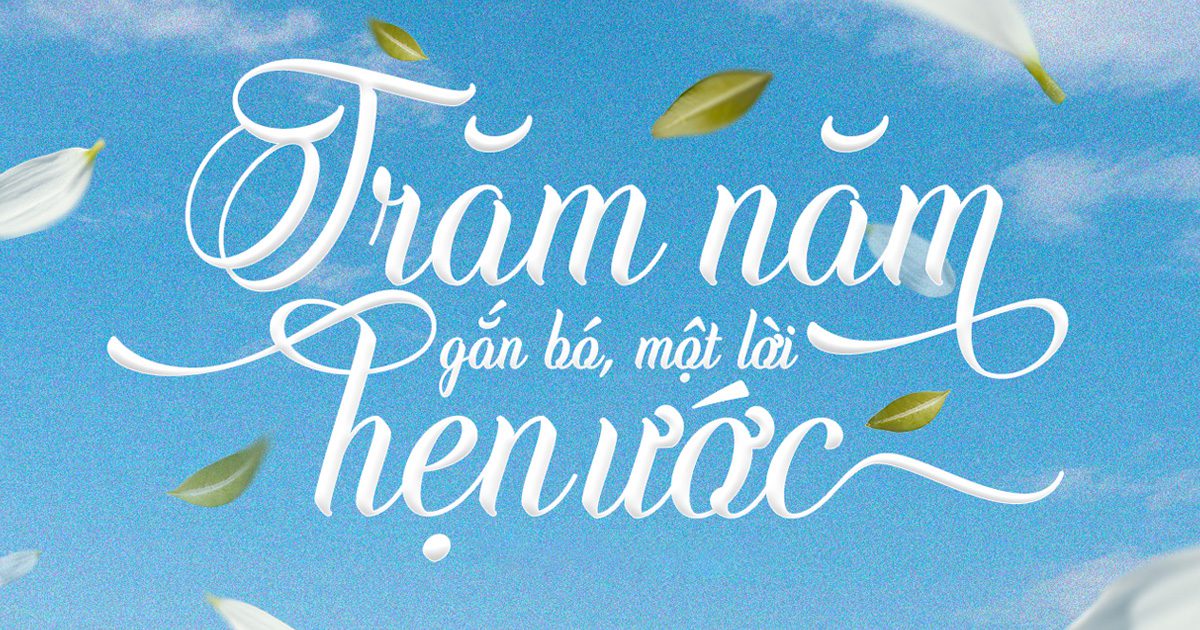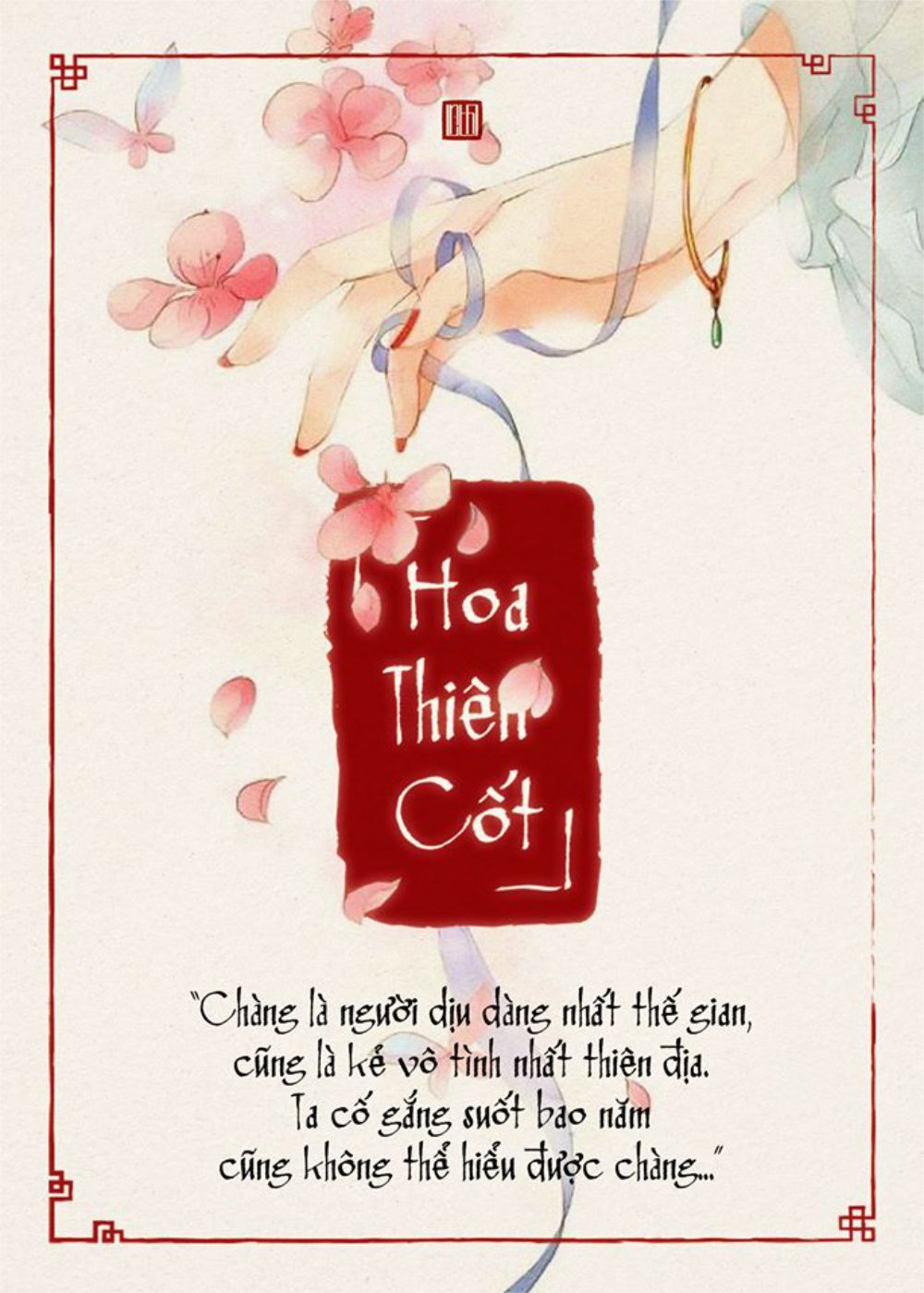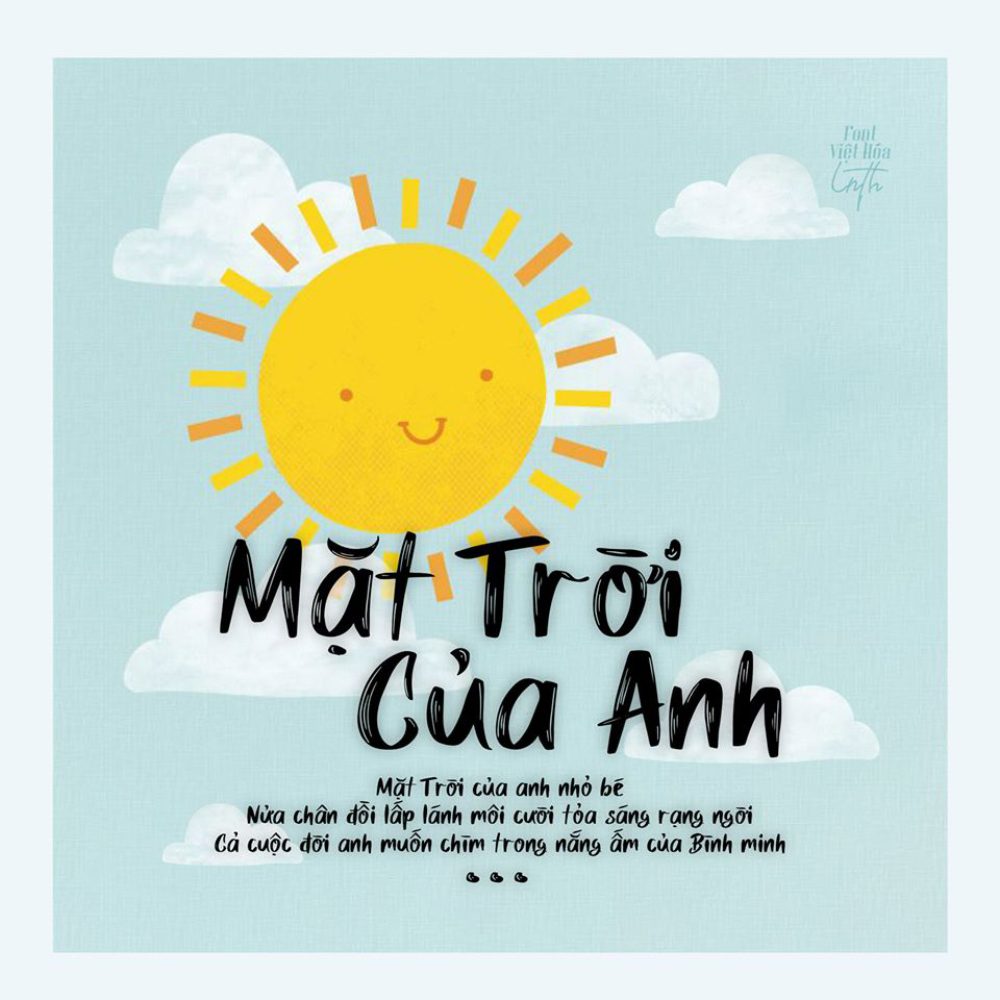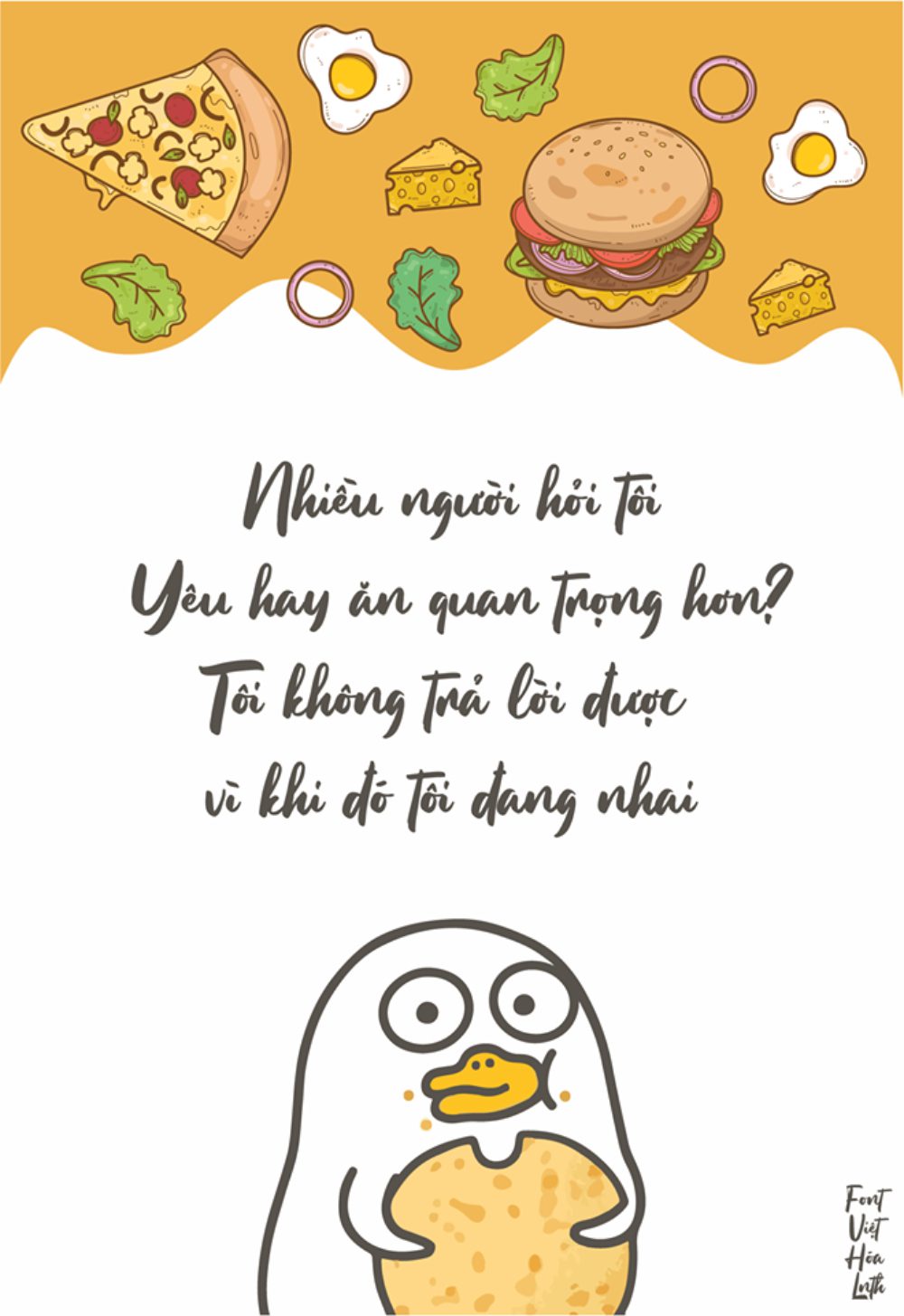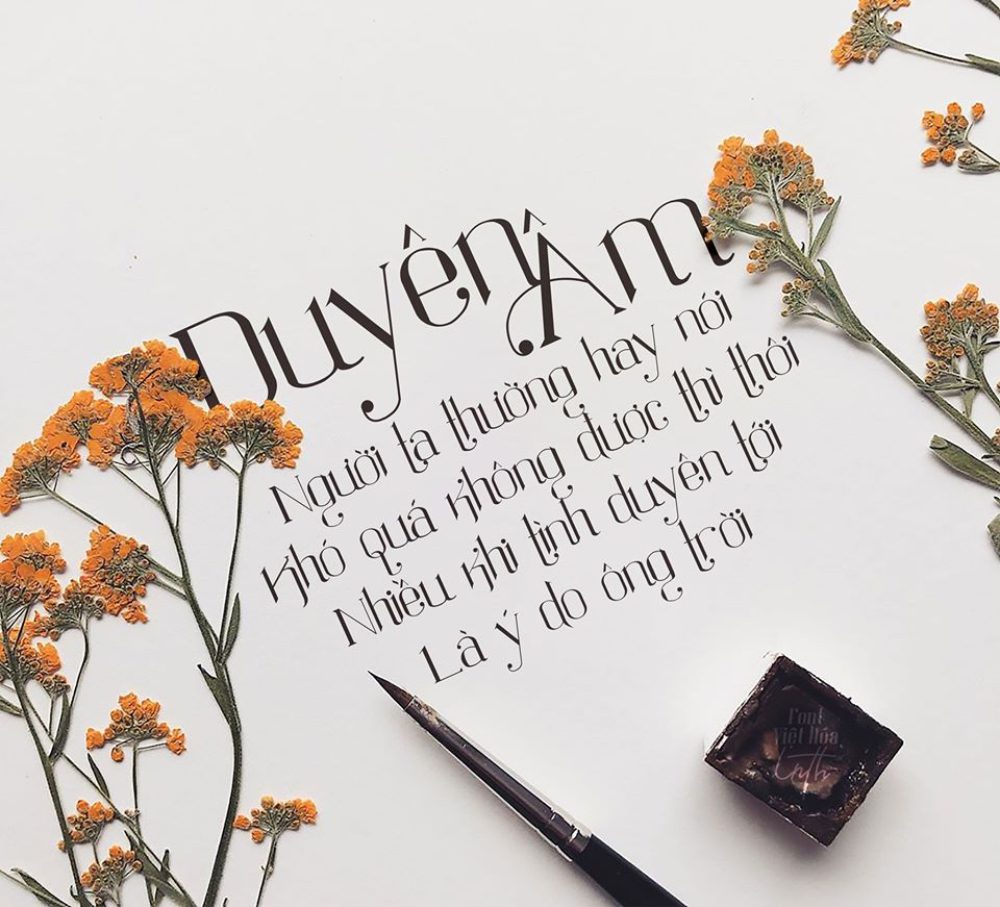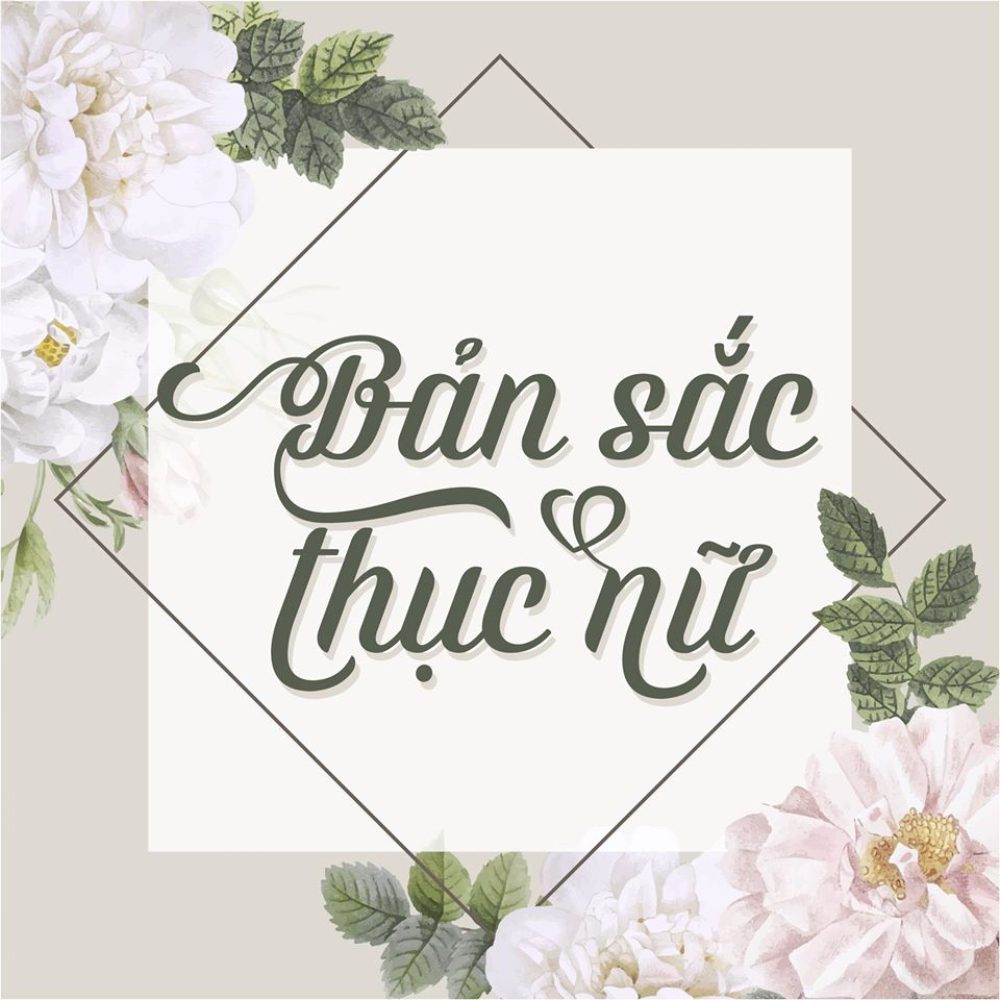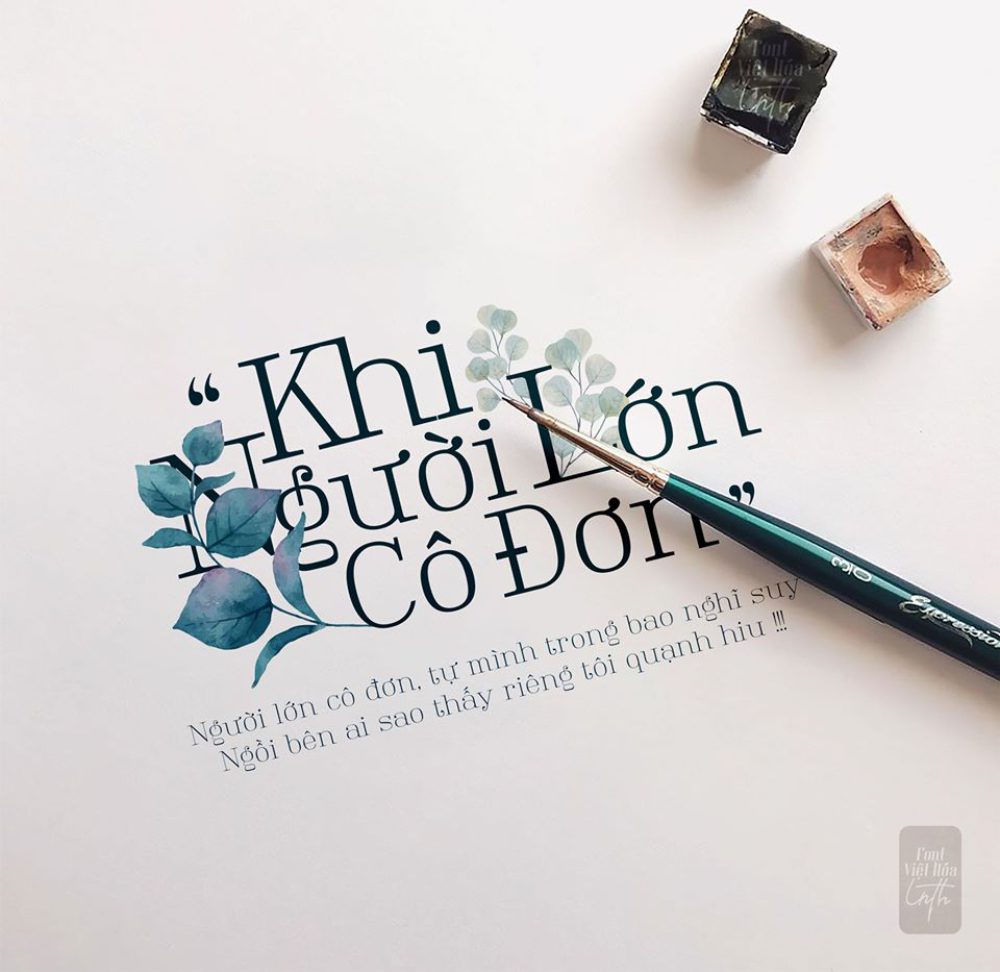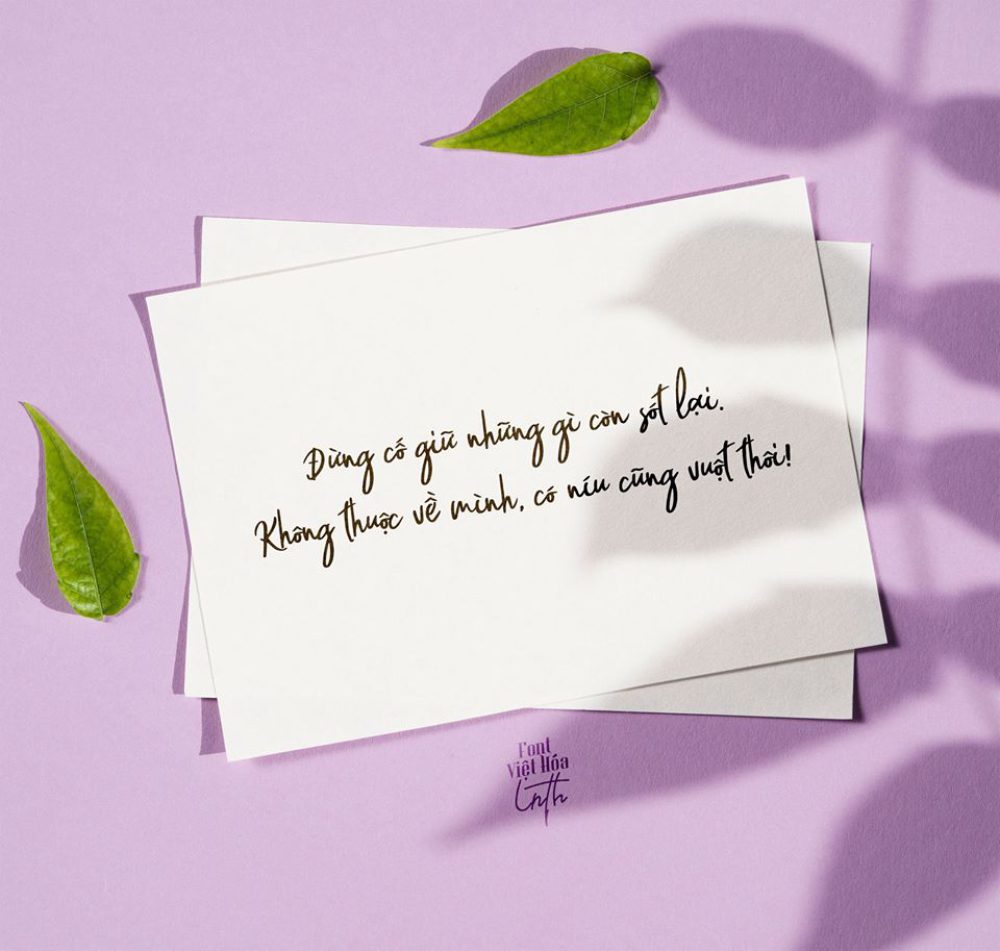
Font Việt Hóa Miễn Phí 39 Font LNTH Cho Designer
Font Việt Hóa Miễn Phí 39 Font LNTH cho designer là bộ tài nguyên chữ rất hữu ích dành cho những ai thường xuyên làm việc với thiết kế đồ họa, truyền thông, branding, poster, banner, social media hoặc các ấn phẩm sáng tạo. Trong thiết kế, font chữ không chỉ có nhiệm vụ hiển thị nội dung mà còn góp phần tạo nên phong cách, cảm xúc và dấu ấn riêng cho từng sản phẩm. Một bộ font đẹp, hỗ trợ tiếng Việt tốt sẽ giúp designer tiết kiệm thời gian, dễ dàng sáng tạo và nâng cao chất lượng thiết kế một cách rõ rệt.
Font LNTH Là Gì?
Font LNTH có thể hiểu là bộ sưu tập các font chữ đã được chọn lọc, thường phục vụ nhu cầu thiết kế đa dạng như tiêu đề, poster, typography, nhận diện thương hiệu, ảnh bìa, banner hoặc các sản phẩm truyền thông số. Với số lượng 39 font, bộ tài nguyên này mang đến nhiều lựa chọn hơn cho designer khi cần thay đổi phong cách thiết kế trong từng dự án.
Điểm đáng chú ý của bộ font này là khả năng hỗ trợ tiếng Việt. Đối với designer Việt Nam, đây là yếu tố rất quan trọng vì nhiều font quốc tế tuy đẹp nhưng không hiển thị tốt dấu tiếng Việt. Khi dùng font chưa được Việt hóa, các ký tự như ă, â, ê, ô, ơ, ư, đ hoặc dấu sắc, huyền, hỏi, ngã, nặng có thể bị lỗi, lệch hoặc mất nét. Vì vậy, việc sử dụng font đã Việt hóa giúp thiết kế trở nên chỉn chu, chuyên nghiệp và dễ ứng dụng hơn.
Vì Sao Designer Nên Sử Dụng Font Việt Hóa?
Hỗ trợ tiếng Việt đầy đủ
Lý do lớn nhất khiến nhiều designer tìm kiếm Font Việt Hóa Miễn Phí là khả năng hiển thị tiếng Việt ổn định. Khi thiết kế poster, banner, logo, menu, catalogue, ảnh quảng cáo hoặc bài đăng mạng xã hội, nội dung tiếng Việt thường xuất hiện nhiều. Nếu font bị lỗi dấu, toàn bộ thiết kế sẽ mất đi sự chuyên nghiệp, dù bố cục hay hình ảnh có đẹp đến đâu.
Font Việt hóa giúp designer yên tâm hơn khi sử dụng cho tiêu đề, slogan, đoạn mô tả ngắn hoặc các nội dung cần hiển thị rõ ràng. Đây là yếu tố đặc biệt quan trọng khi thiết kế cho khách hàng, thương hiệu, cửa hàng hoặc các dự án cần in ấn.
Đa dạng phong cách thiết kế
Bộ 39 Font LNTH mang đến nhiều kiểu chữ khác nhau, giúp designer linh hoạt hơn trong quá trình sáng tạo. Tùy vào từng dự án, bạn có thể chọn font mạnh mẽ, hiện đại, tối giản, cổ điển, nghệ thuật, viết tay hoặc cá tính. Sự đa dạng này giúp mỗi thiết kế có phong cách riêng, tránh cảm giác lặp lại hoặc nhàm chán.
Ví dụ, với thiết kế thương hiệu cao cấp, bạn có thể chọn font serif thanh lịch. Với poster sự kiện trẻ trung, font display hoặc sans-serif đậm sẽ phù hợp hơn. Với các thiết kế mang cảm xúc nhẹ nhàng, font viết tay hoặc font mềm mại có thể giúp nội dung trở nên gần gũi hơn.
39 Font LNTH Phù Hợp Cho Những Dự Án Nào?
Thiết kế poster và banner
Poster và banner là những ấn phẩm cần tiêu đề nổi bật, dễ đọc và có khả năng thu hút ánh nhìn nhanh. Một font phù hợp sẽ giúp thông điệp chính trở nên mạnh mẽ hơn, đồng thời tạo điểm nhấn cho toàn bộ bố cục. Với bộ 39 Font LNTH, designer có thể lựa chọn nhiều kiểu chữ khác nhau để phù hợp với từng chủ đề như thời trang, sự kiện, âm nhạc, giáo dục, quảng cáo, nghệ thuật hoặc truyền thông thương hiệu.
Khi thiết kế poster, bạn nên dùng font nổi bật cho tiêu đề chính và font đơn giản hơn cho phần nội dung phụ. Cách kết hợp này giúp bố cục vừa có điểm nhấn, vừa đảm bảo người xem dễ đọc thông tin.
Thiết kế logo và nhận diện thương hiệu
Font chữ đóng vai trò quan trọng trong thiết kế logo và nhận diện thương hiệu. Một font đẹp có thể giúp thương hiệu trở nên chuyên nghiệp, dễ nhớ và có cá tính riêng. Với các font đã hỗ trợ tiếng Việt, designer có thể dễ dàng tạo logo cho thương hiệu Việt, shop online, quán cà phê, studio, spa, mỹ phẩm, thời trang hoặc sản phẩm thủ công.
Tuy nhiên, khi dùng font miễn phí cho logo thương mại, bạn nên kiểm tra kỹ giấy phép sử dụng. Một số font có thể miễn phí cho mục đích cá nhân nhưng cần license riêng nếu dùng cho thương hiệu hoặc sản phẩm kinh doanh.
Thiết kế social media
Trong môi trường mạng xã hội, hình ảnh cần nổi bật trong thời gian rất ngắn. Font chữ đẹp, rõ ràng và đúng phong cách sẽ giúp bài đăng Facebook, Instagram, Zalo, TikTok cover hoặc thumbnail YouTube thu hút hơn. Bộ 39 Font LNTH có thể hỗ trợ designer tạo nhiều dạng nội dung khác nhau như bài quảng cáo, quote, thông báo khuyến mãi, ảnh bìa, poster mini hoặc nội dung truyền thông hằng ngày.
Với social media, bạn nên ưu tiên font dễ đọc ở kích thước nhỏ, tránh dùng font quá mảnh hoặc quá nhiều chi tiết nếu nền ảnh phức tạp.
Ưu Điểm Của Bộ Font Việt Hóa Miễn Phí 39 Font LNTH
Tiết kiệm thời gian tìm kiếm font
Việc tìm từng font riêng lẻ có thể mất khá nhiều thời gian, đặc biệt khi designer cần font vừa đẹp vừa hỗ trợ tiếng Việt. Một bộ font được tổng hợp sẵn sẽ giúp bạn tiết kiệm công sức, dễ dàng thử nhiều lựa chọn và nhanh chóng tìm ra kiểu chữ phù hợp cho dự án.
Khi có sẵn bộ font trong thư viện cá nhân, bạn có thể làm việc nhanh hơn, đặc biệt trong những dự án cần chỉnh sửa nhiều phương án hoặc cần hoàn thiện thiết kế trong thời gian ngắn.
Dễ ứng dụng trong nhiều phong cách
Một bộ font chất lượng không chỉ đẹp khi nhìn riêng lẻ mà còn phải dễ ứng dụng trong thực tế. 39 Font LNTH có thể được dùng trong nhiều dạng thiết kế khác nhau, từ tiêu đề lớn, poster quảng cáo, typography, banner website cho đến các ấn phẩm in ấn. Sự linh hoạt này giúp designer tận dụng font tốt hơn thay vì chỉ dùng được cho một vài trường hợp nhất định.
Phù hợp cho cả người mới và designer chuyên nghiệp
Người mới học thiết kế có thể sử dụng bộ font này để làm quen với cách lựa chọn và phối font. Trong khi đó, designer chuyên nghiệp có thể dùng để mở rộng thư viện tài nguyên, tăng tốc quy trình làm việc và tạo ra nhiều phong cách thiết kế đa dạng hơn.
Cách Sử Dụng Font LNTH Hiệu Quả
Kiểm tra font trước khi dùng
Dù là Font Việt Hóa Miễn Phí, bạn vẫn nên kiểm tra kỹ từng font trước khi đưa vào thiết kế chính thức. Hãy thử các câu tiếng Việt có nhiều dấu như “Thiết kế sáng tạo”, “Khuyến mãi đặc biệt”, “Bộ nhận diện thương hiệu” để xem font có hiển thị ổn định hay không.
Việc kiểm tra trước giúp tránh lỗi khi xuất file, in ấn hoặc bàn giao thiết kế cho khách hàng. Đây là thói quen cần thiết để đảm bảo sản phẩm cuối cùng luôn chỉn chu.
Không dùng quá nhiều font trong một thiết kế
Một lỗi thường gặp của người mới là sử dụng quá nhiều font trong cùng một bố cục. Điều này khiến thiết kế bị rối mắt và thiếu sự đồng bộ. Thông thường, bạn chỉ nên dùng 2 đến 3 font: một font cho tiêu đề chính, một font cho nội dung phụ và có thể thêm một font nhấn nếu cần.
Khi phối font, hãy tạo sự tương phản hợp lý. Ví dụ, tiêu đề có thể dùng font đậm, mạnh mẽ; phần mô tả dùng font đơn giản, dễ đọc. Cách này giúp thiết kế vừa nổi bật vừa chuyên nghiệp.
Chú ý đến khoảng cách chữ và dòng
Font đẹp nhưng nếu khoảng cách chữ, khoảng cách dòng hoặc kích thước không hợp lý thì thiết kế vẫn có thể khó đọc. Khi dùng font cho tiêu đề, hãy điều chỉnh spacing để chữ thoáng hơn. Với nội dung dài, cần chú ý line-height để người xem đọc dễ hơn.
Đặc biệt, khi dùng font display hoặc font viết tay, bạn nên kiểm tra kỹ ở nhiều kích thước khác nhau để đảm bảo chữ không bị dính, rối hoặc mất chi tiết.
Lưu Ý Về Bản Quyền Khi Sử Dụng Font
Khi tải font miễn phí, bạn cần kiểm tra giấy phép sử dụng đi kèm. Không phải font miễn phí nào cũng được phép dùng cho mục đích thương mại. Một số font chỉ cho phép dùng trong dự án cá nhân, trong khi thiết kế logo, bao bì, quảng cáo hoặc sản phẩm bán hàng có thể yêu cầu license riêng.
Việc tôn trọng bản quyền font không chỉ giúp tránh rủi ro pháp lý mà còn thể hiện sự chuyên nghiệp của designer. Nếu bạn dùng font cho khách hàng hoặc thương hiệu, hãy ưu tiên những font có thông tin license rõ ràng.
Font Việt Hóa Miễn Phí
Kết Luận
Font Việt Hóa Miễn Phí 39 Font LNTH cho designer là bộ tài nguyên đáng tham khảo nếu bạn đang cần thêm nhiều lựa chọn font chữ đẹp, hỗ trợ tiếng Việt và dễ ứng dụng trong thiết kế. Với số lượng 39 font đa dạng, bộ tài nguyên này phù hợp cho poster, banner, logo, social media, typography, branding và nhiều dự án sáng tạo khác.
Khi sử dụng, bạn nên kiểm tra khả năng hiển thị tiếng Việt, chọn font phù hợp với từng phong cách, phối font hợp lý và chú ý đến giấy phép sử dụng. Một bộ font được chọn lọc tốt sẽ giúp designer tiết kiệm thời gian, nâng cao chất lượng thiết kế và tạo ra những ấn phẩm chuyên nghiệp, cuốn hút hơn.